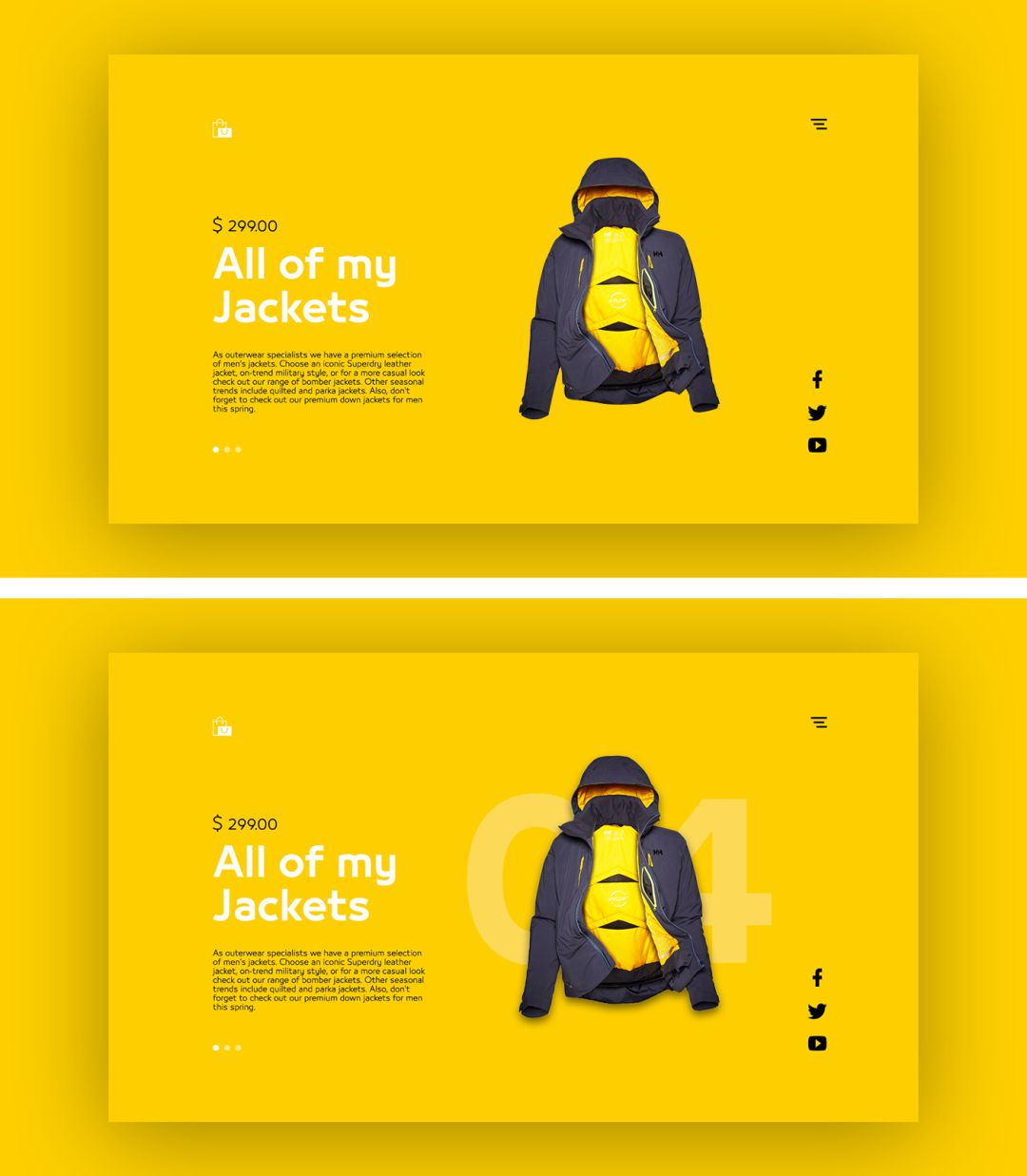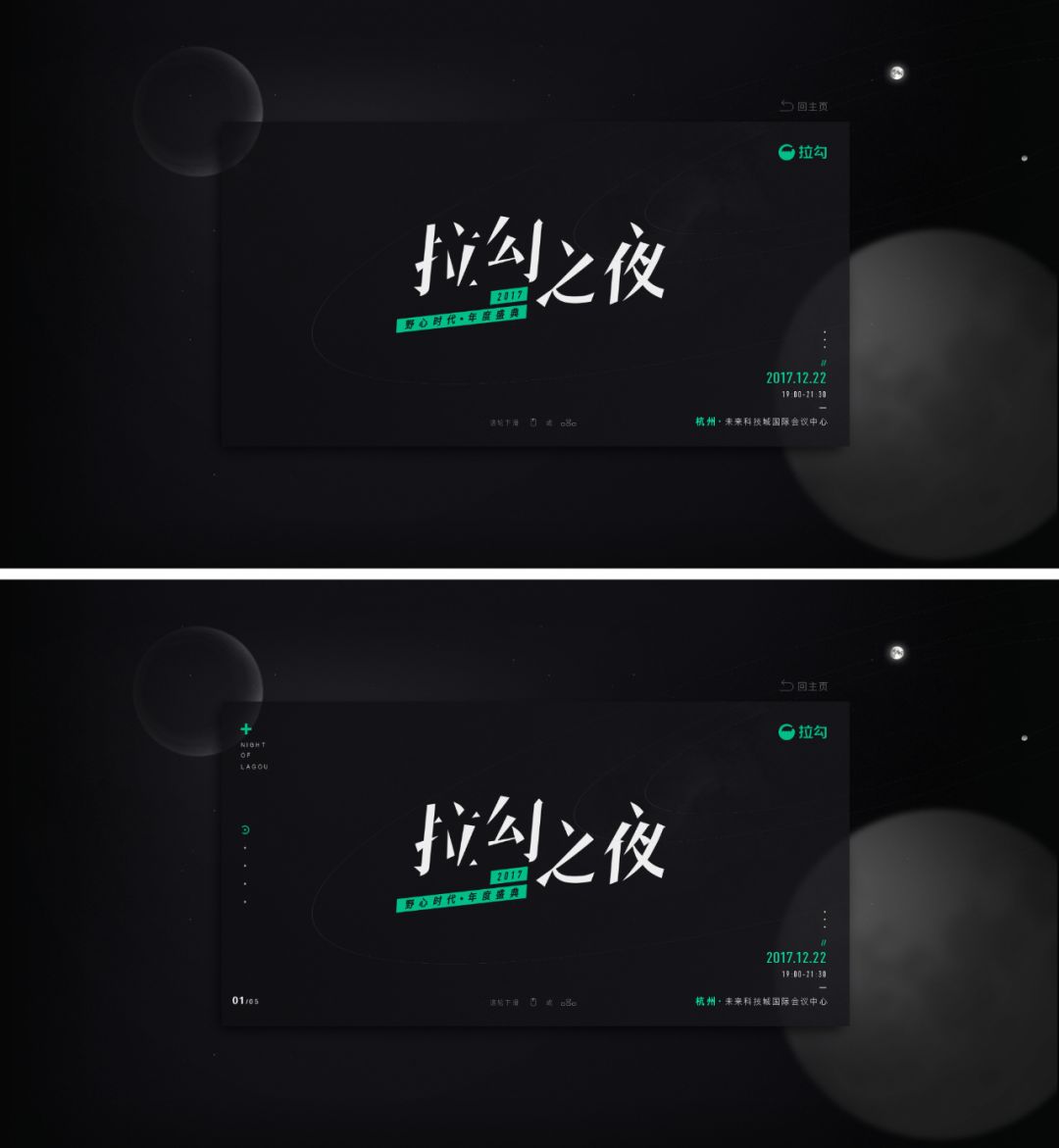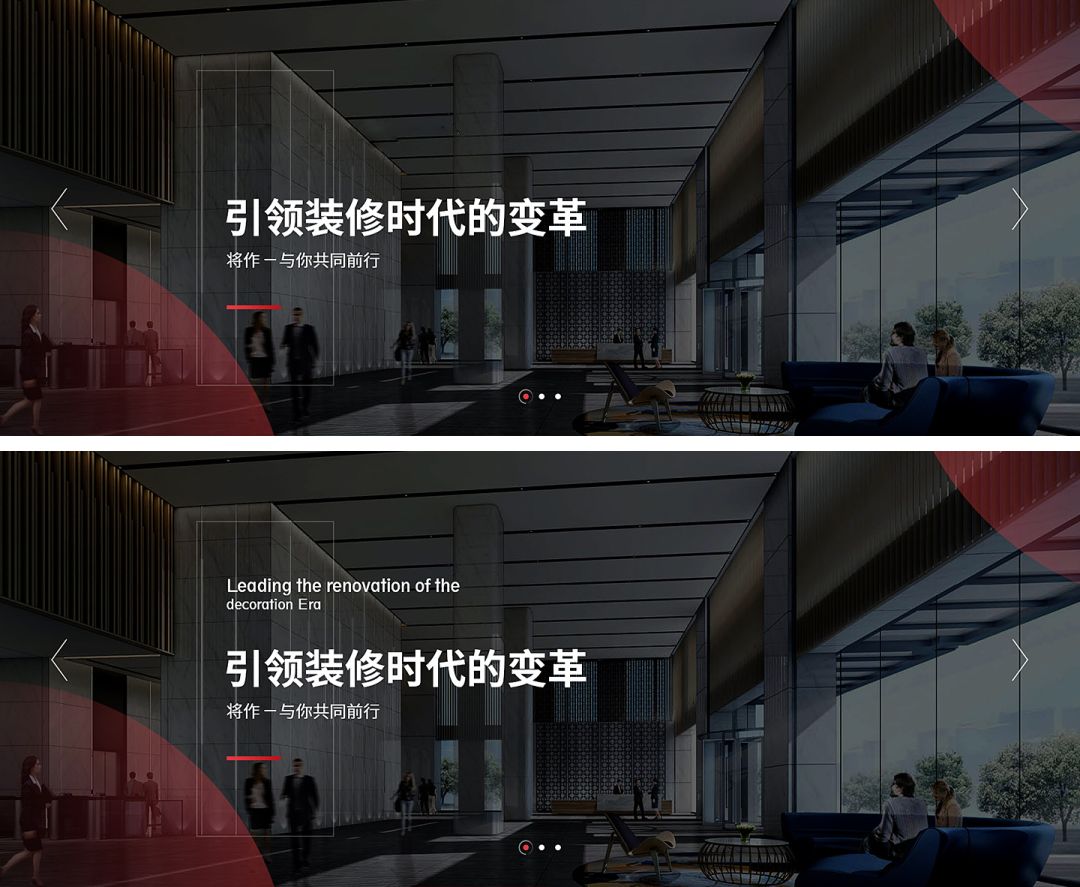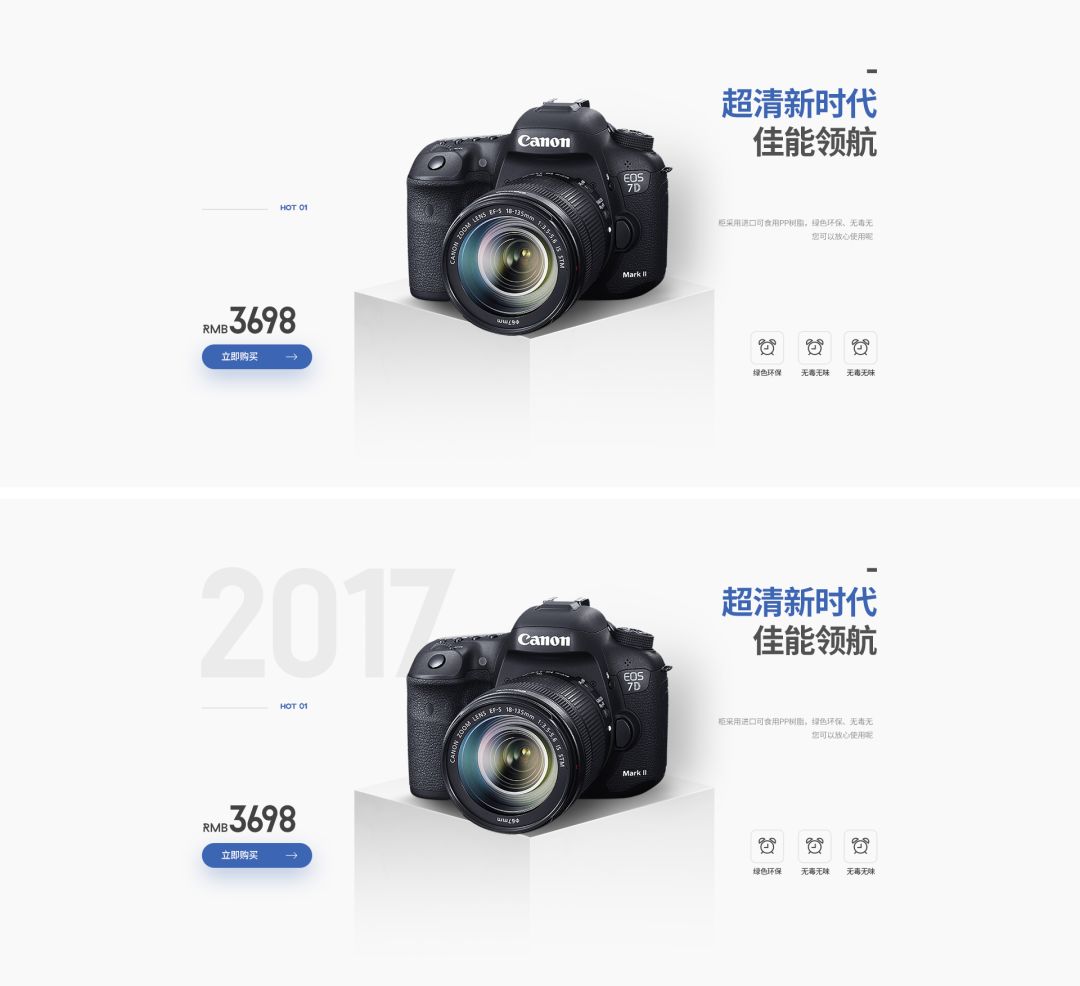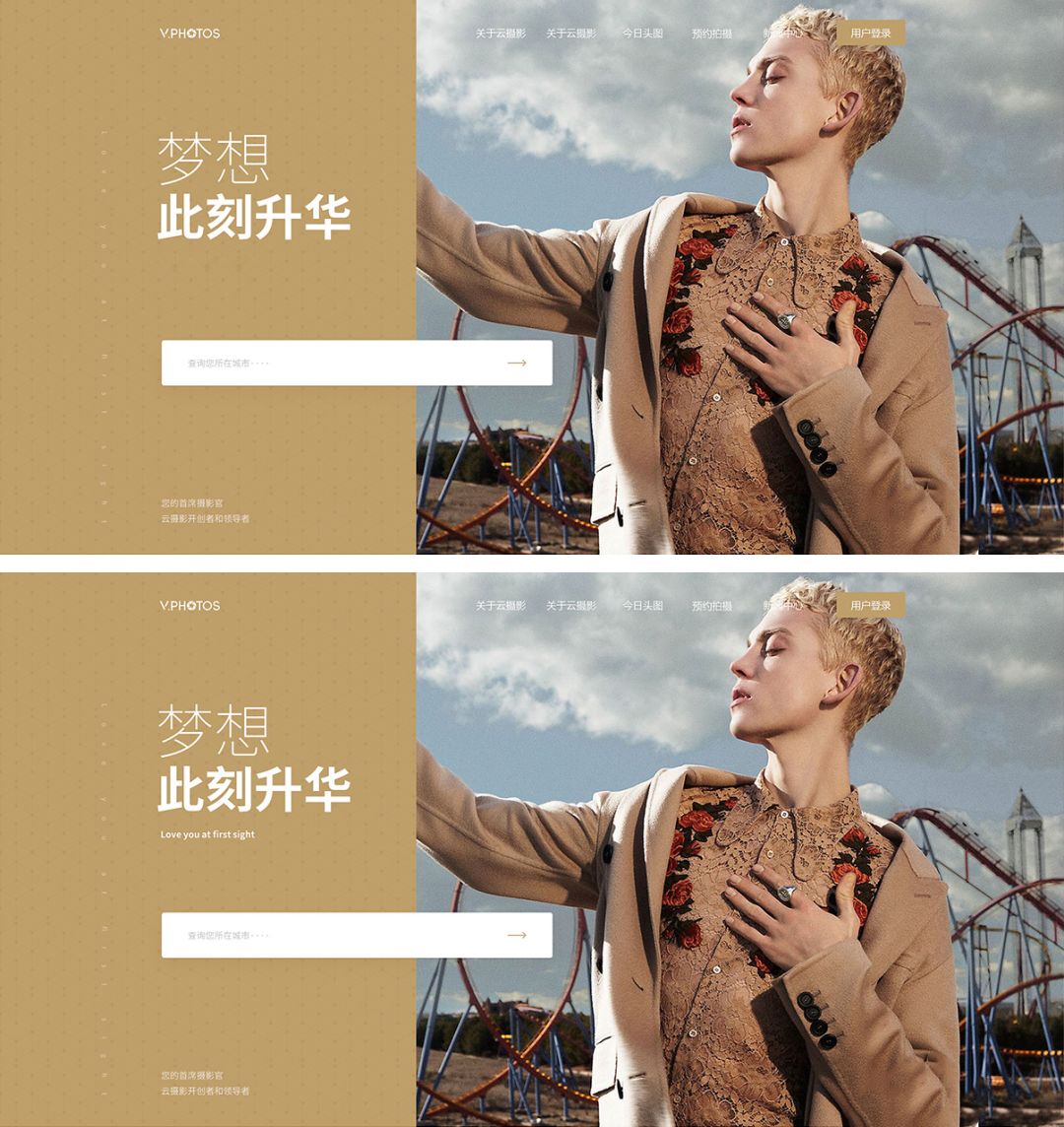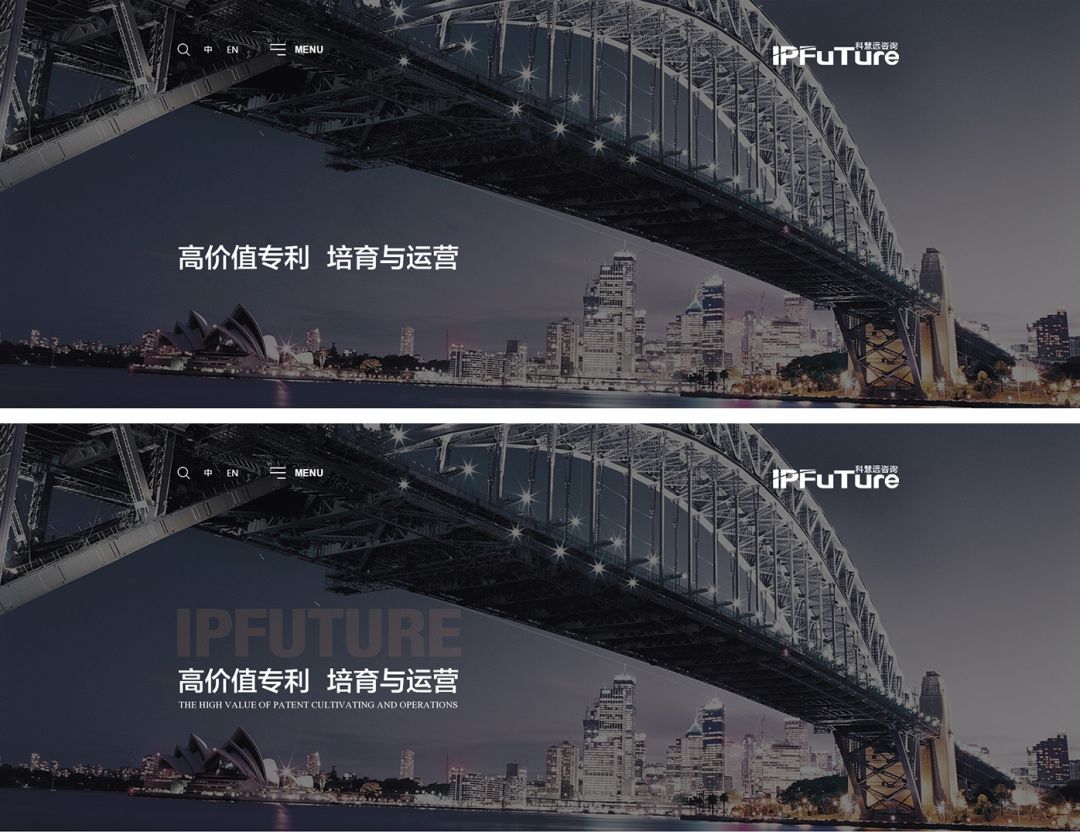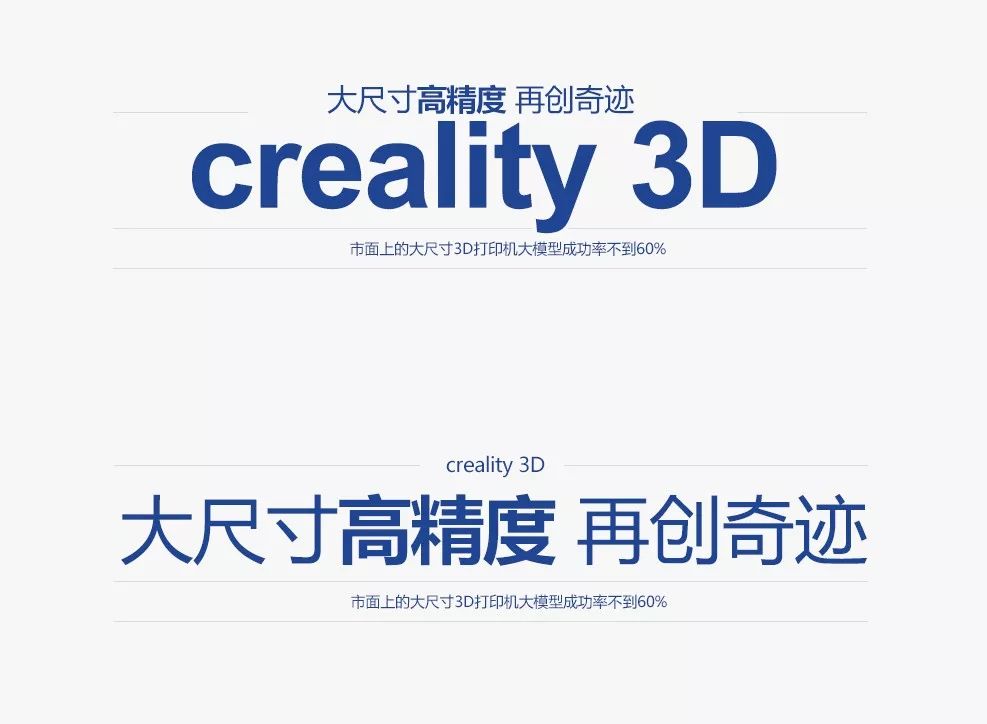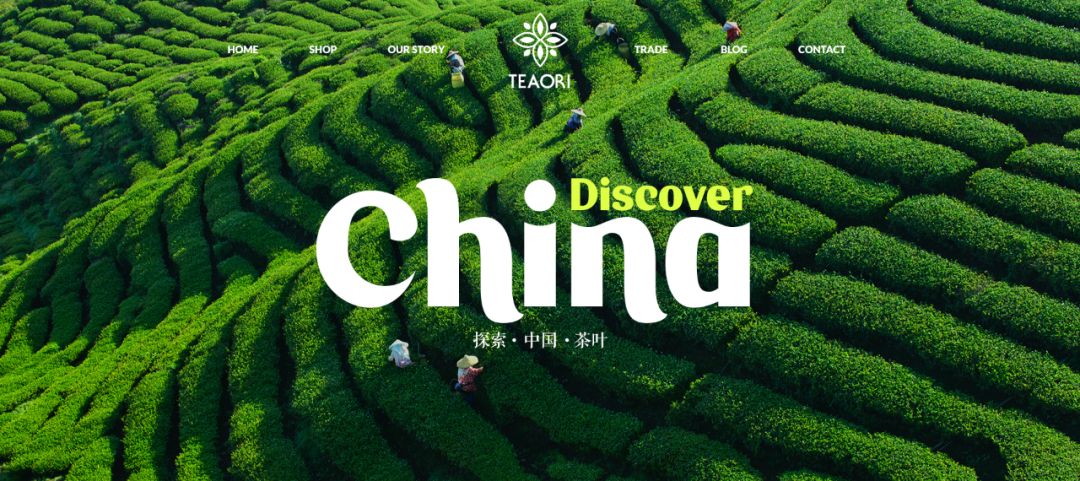
解决画面空、没有层次感,可以试试英文字体
在很多优秀的设计作品中,我们常常会看到一些英文的出现,形态上也各不相同:小到不仔细就看不到、大到比产品还大,这也会导致甲方会不理解,“你放这么大的英文不是在抢我们的产品主体吗?”,“这么小的英文给谁看的,都看不见,还不如不加!”
面对这种外行的指教,你要做的就是用案例说话~
当作品内容感缺失、视觉重心不稳定、画面空等情况出现时,可以用英文去填充,常用的英文可以是关键字或词的翻译、LOGO、数字,比如:
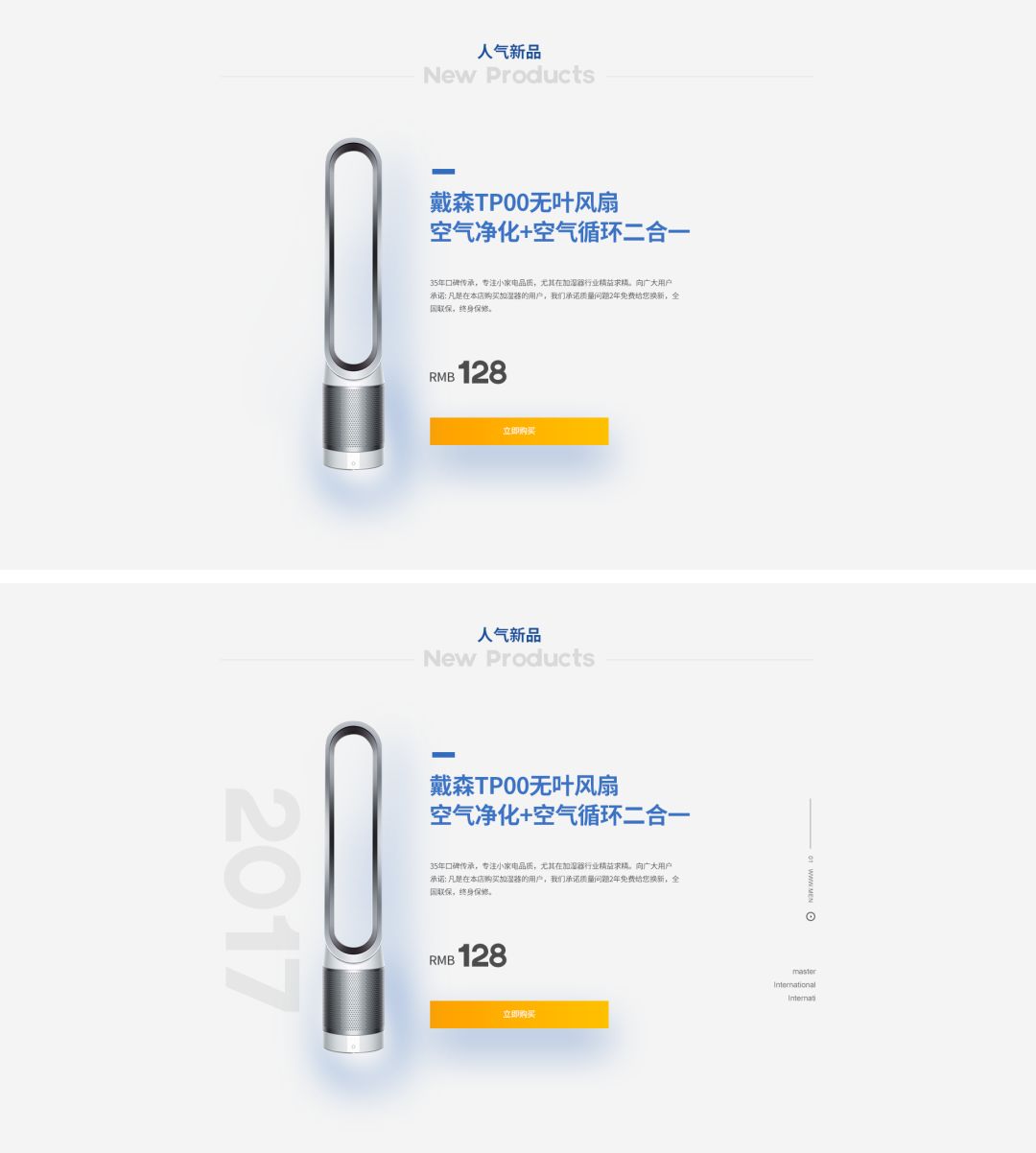
不过英文作为填充存在时,需要注意:
第一:英文的存在不能抢主体,因为此类英文最主要的目的只是为了填充多余留白,增加内容感,并不属于主体信息所必需的,仅作为次要元素存在!
第二:大字号的填充英文在一个画面中最多出现1-2处即可:常用方式给10%左右的透明度,不易太明显,能起到填充作用即可,而小字号的填充英文,要尽可能做到不喧宾夺主,可以英文和图形结合使用。
第三:无论大字号还是小字号,都要尽量做到视觉重心稳定。
如果日常工作中,遇到文字信息太少,不会排版的情况,可以运用不同大小的英文作为辅助,增加层次感和精致感,比如:
针对文字排版我们可以总结:
第一:当文字排版缺少对比且又没有足够的文案填充时,英文翻译就可以起到填充及增加对比的作用,避免排版单一、缺少变化,具体英文字号的大小要根据实际情况而定!
第二:当排版缺少层次感或分组太少时,同样可以通过英文翻译来解决,因为我们常用的排版至少分为两组,三组是最合理的
还有一种情况(非文字排版),也可以通过装饰性英文,增加画面层次感,比如:
英文对我们来说是图形大于文字,具备一定的形式感,所以不妨尝试增加英文或者是放大英文,甚至可以将英文作为文字排版的重点,从而提升整体的设计感,比如:
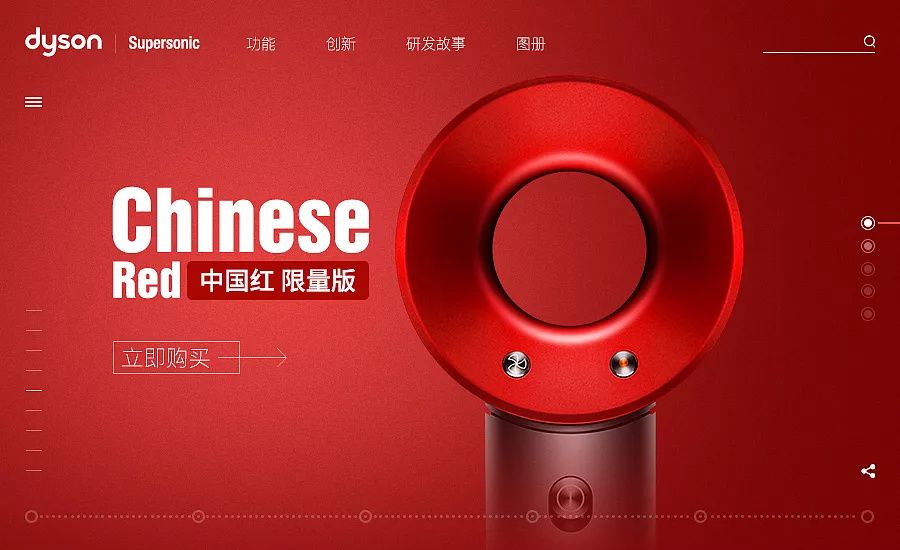
但这类形式适用于文案信息相对较少的情况下,如果文案信息量很大且又采用这种形式,很容易让用户忽略掉主要的文案信息,反而阻碍了正常的信息传达,侧重点很重要,看下面这个案例~
同样的文案,不一样的排版形式,两种不同的视觉感受:第一种以英文为切入点的,给人的形式感更强、且视觉上比较新颖,第二种以主文案信息为切入点,版式上更加整齐,属于常见的一种形式,两者排版并没有全完的好与坏,只是有一定的视觉反差对比,具体用何种形式,完全取决于设计师!
英文作为图形出现在画面中,应该是最顺理成章了,你可以结合产品、材质、纹理、颜色,再通过穿插、叠加的手法,增加整体的丰富度,比如:
当我们的作品出现画面空、缺少形式感、对比不够强烈等情况时,可以适当的运用英文、数字、形状进行填充,根据不同目的,选择不同形态的英文,比如:画面空,就适合运用小字号英文或者大字号英文打透明度的形式;而当因画面缺少形式感而使用英文时,则需要把英文做得稍微明显一些,甚至可以直接作为视觉重点、图形的形式;当然,常用的英文不仅只有这些作用,还有固定视觉范围的作用,比如:
图二选用的是英文图形结合的形式,既填充了空白,也起到了固定视觉范围的作用,比图三仅仅使用边框约束,整体效果要好,所以,要因需而用英文字体,下课!